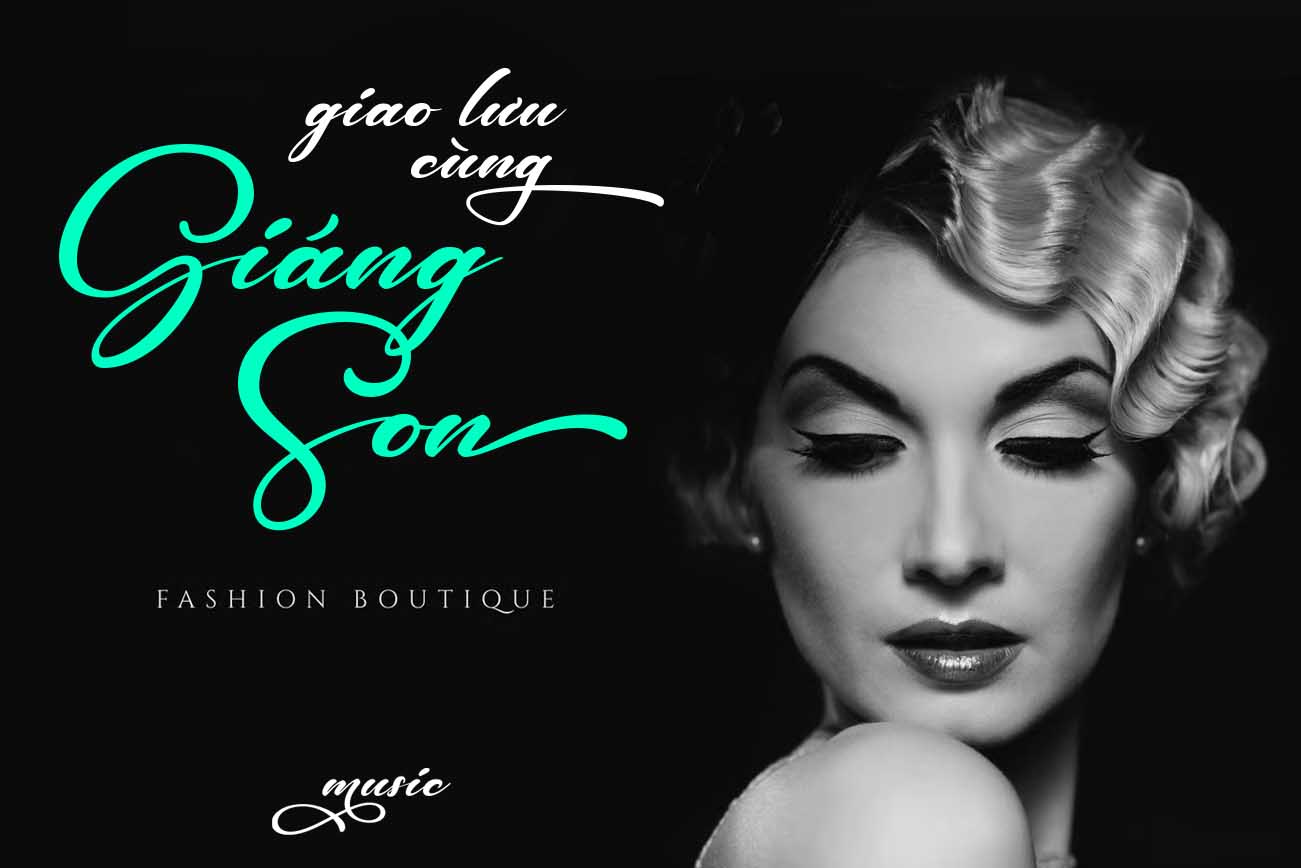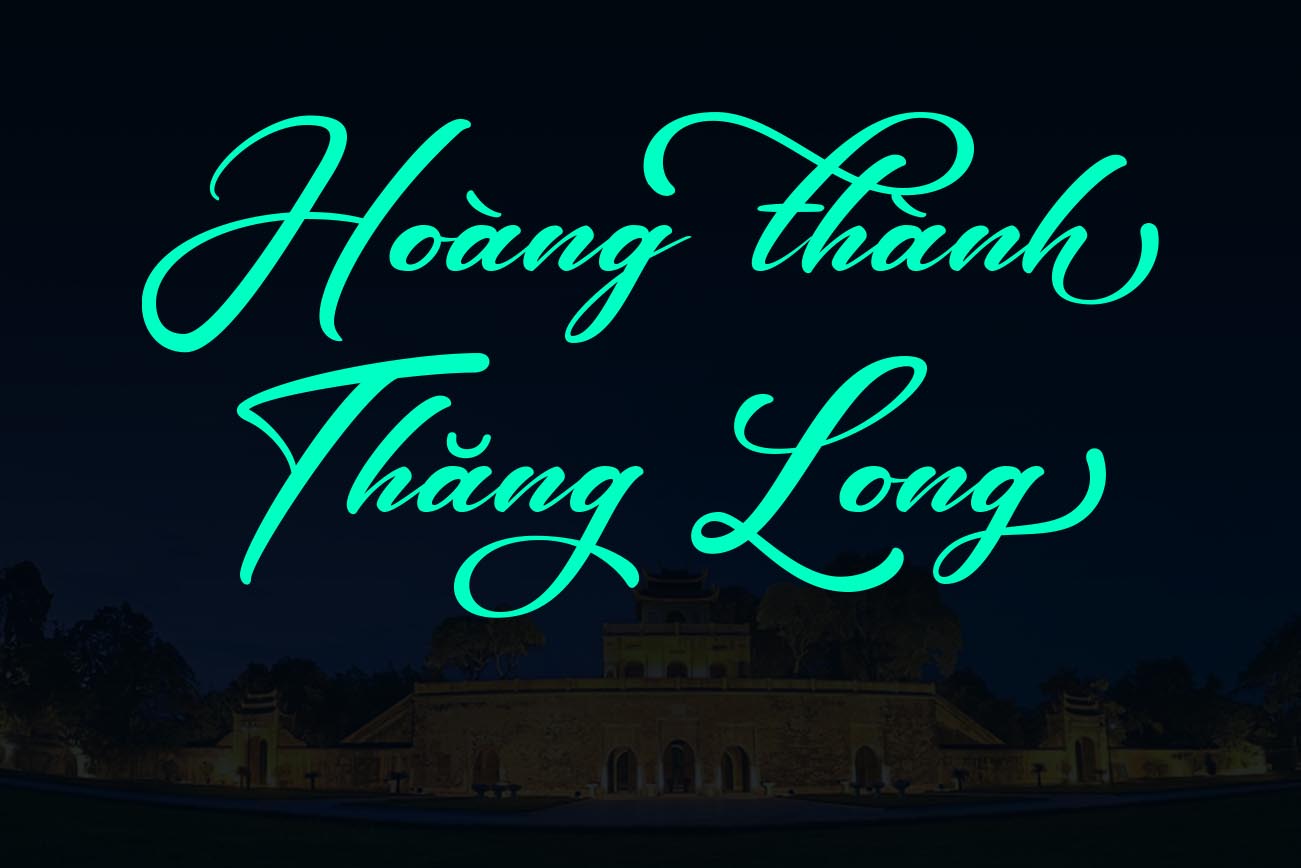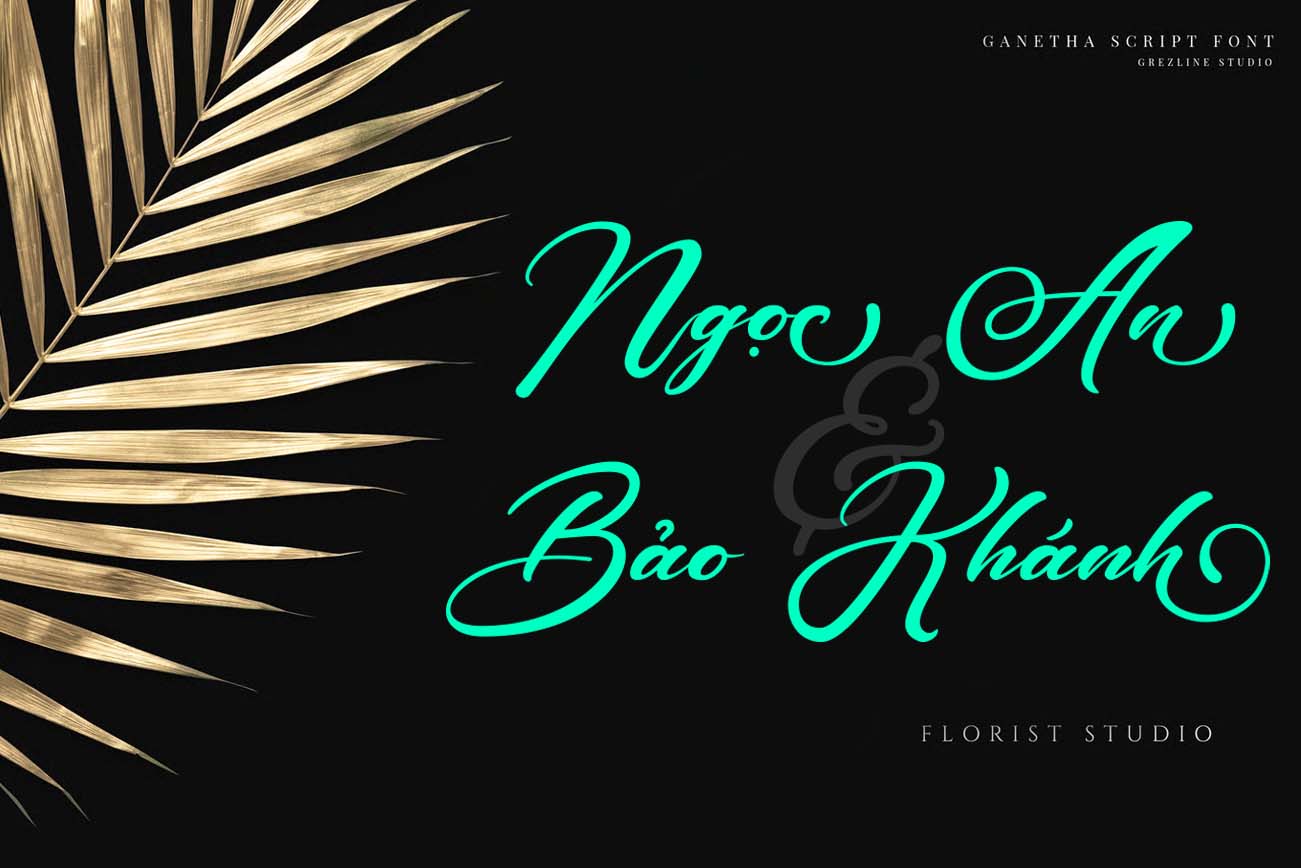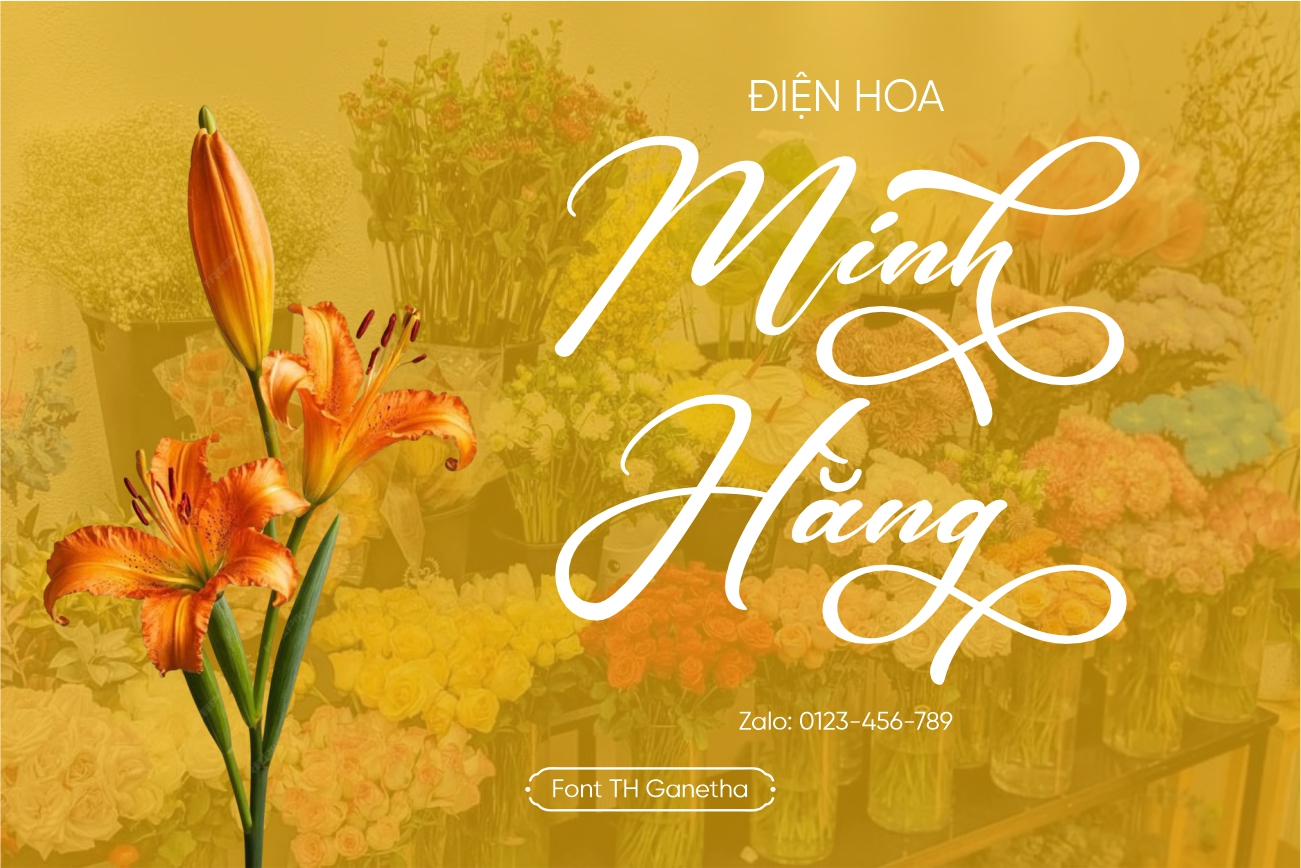
Trong xu hướng thiết kế ngày cưới hiện đại, TH Ganetha nổi lên như một câu trả lời hoàn hảo cho các tác phẩm cần truyền tải trọn vẹn cảm xúc lãng mạn. Là phiên bản Việt hóa hoàn chỉnh từ bộ font Ganetha đình đám, font chữ mang đậm phong cách thư pháp (Calligraphy) thủ công này giữ trọn vẹn cái hồn tinh tế nguyên bản, đồng thời tương thích hoàn hảo với dấu tiếng Việt nhờ sự chăm chút kỹ lưỡng từ Team TH.
Hệ thống ký tự phong phú: Sở hữu hơn 820 ký tự gốc (glyphs) cùng hệ thống ký tự thay thế (Alternates) đa dạng, cho phép tùy biến các nét gạch chân, nét uốn lượn đầu - cuối cực kỳ linh hoạt.
Font Wedding lý tưởng: Sự uyển chuyển trong từng nét nối giúp tên cô dâu - chú rể hiện lên như một tác phẩm nghệ thuật độc bản, mang lại cảm giác sang trọng, cổ điển cho không gian tiệc cưới Luxury.
Lựa chọn đắt giá cho Branding: Hiệu ứng thị giác chau chuốt và đẳng cấp của font chữ này cực kỳ phù hợp cho logo tiệm hoa, bao bì mỹ phẩm cao cấp hay các hình ảnh trích dẫn (Quote) trên mạng xã hội.
Nếu bạn đang tìm kiếm một công cụ để "thổi hồn" vào các thiết kế cần sự bay bổng và sang trọng, TH Ganetha chắc chắn là mảnh ghép không thể thiếu.